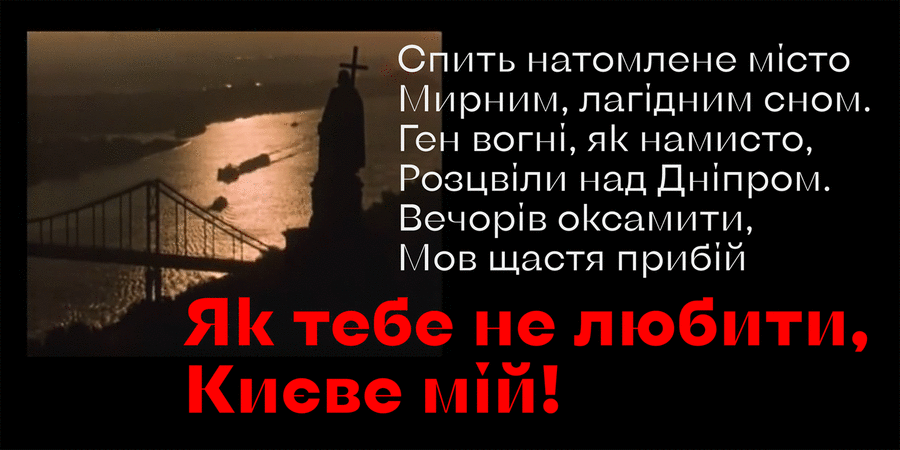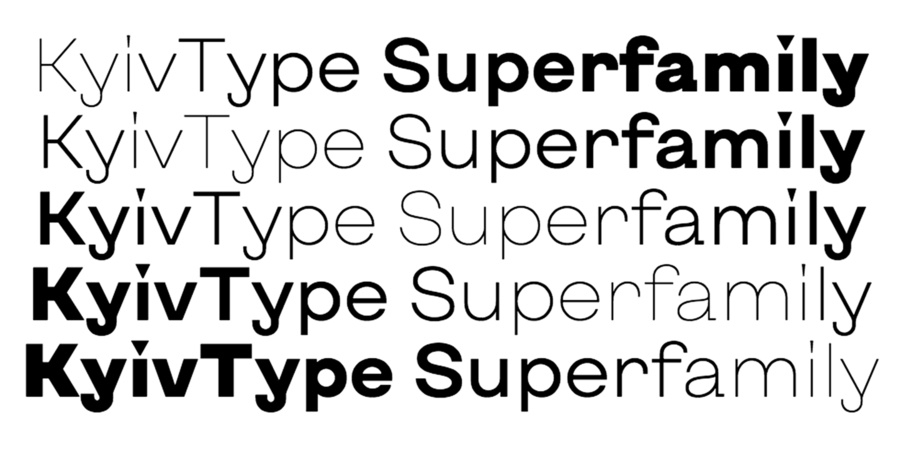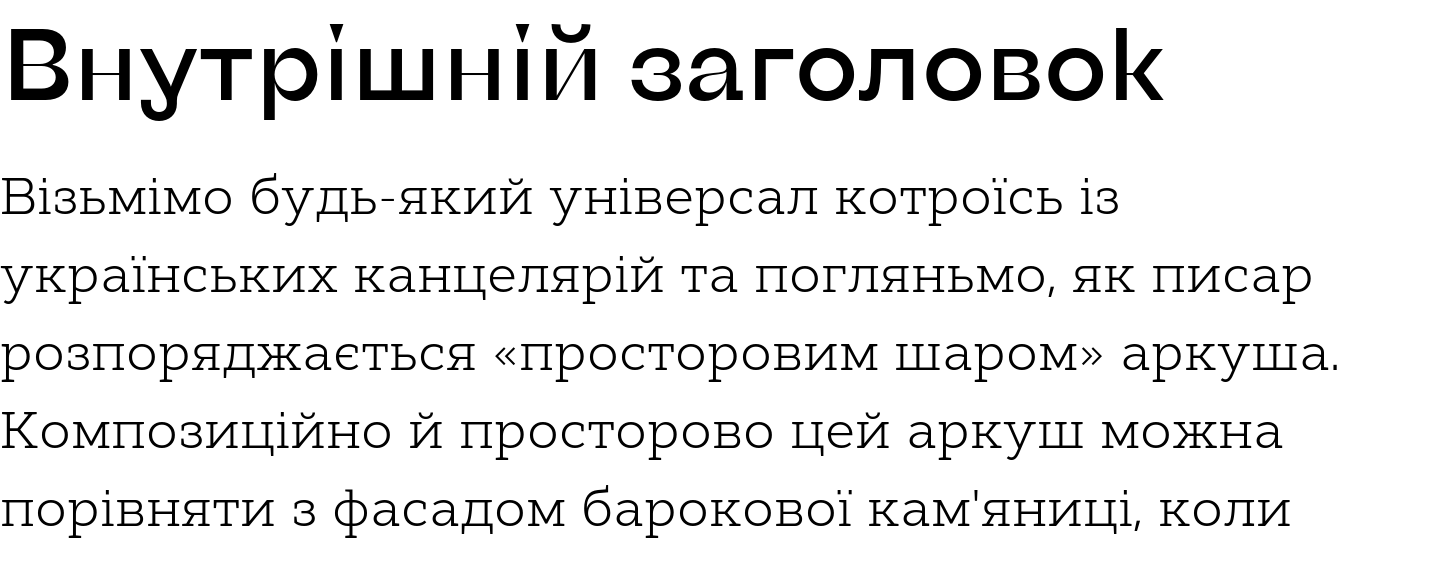
Kyiv Type Sans (1 шрифт)
Ґротескова частина супергарнітури для Києва. Шрифт для Києва з багатьма обличчями та крутим характером з'явився тоді, коли до проекту #newkyivlogo (каштановий лист як логотип Києва) приєднався Дмитро Растворцев. «Київ різний. Трохи брутальний. Трохи інтелігентний. Трохи тусовочний. Трохи хіпстерський. Трохи традиційний. Це еклектичне місто. Воно легко включає різне та різних – це створює той Київ, який я люблю. Шрифт такий самий – трохи брутальний, трохи інтелігентний, трохи тусовочний, трохи традиційний, трохи дикий. І дуже-дуже різний.» – так описує проект Олександр Трегуб – засновник Projector та ідейний натхненник нового логотипу Києва.
Kyiv*Type створений з любов'ю до Києва, за підтримки Banda, Bulanov creative büro та Projector. Шрифт розробив Дмитро Растворцев у 2019-2020 році.
Асоціації з сімейством шрифтів Kyiv Type SansОсобистість і характер гарнітури:
статичний, стійкий, глобалізований, глобалістічний, міський, якісний, сучасний, модний, технічний, оригінальний, міцний, мужній, помітний, яскравий, сміливий, точний, рівний, практичний, твердий, надійний, впевнений, сильний, інженерний, індустріальний, жорсткий, грубий, різкий, чіткий, архітектурний, чистий, прохолодний, свіжий, ефектний, культурний, гладенький, прямий, сталевий, формальний, цікавий
дизайн, Місто, одяг, взуття, математика, урбаністика, техніка, тара, креслення, конструктор, архітектура, коворкінг, банкнота, монета, мода, архітектор, меморіал, пам'ятник, музей, скульптура, туризм Гарнітура має ознаки стилів: